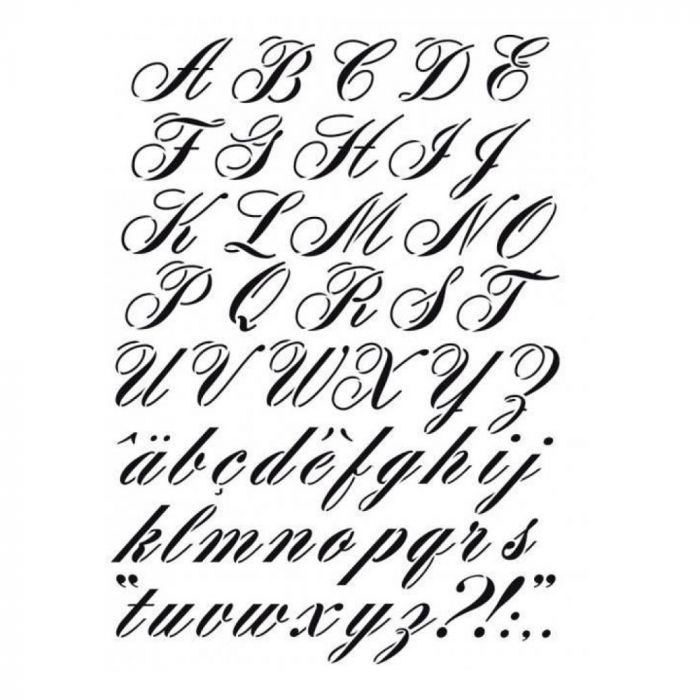
Police d'écriture italique
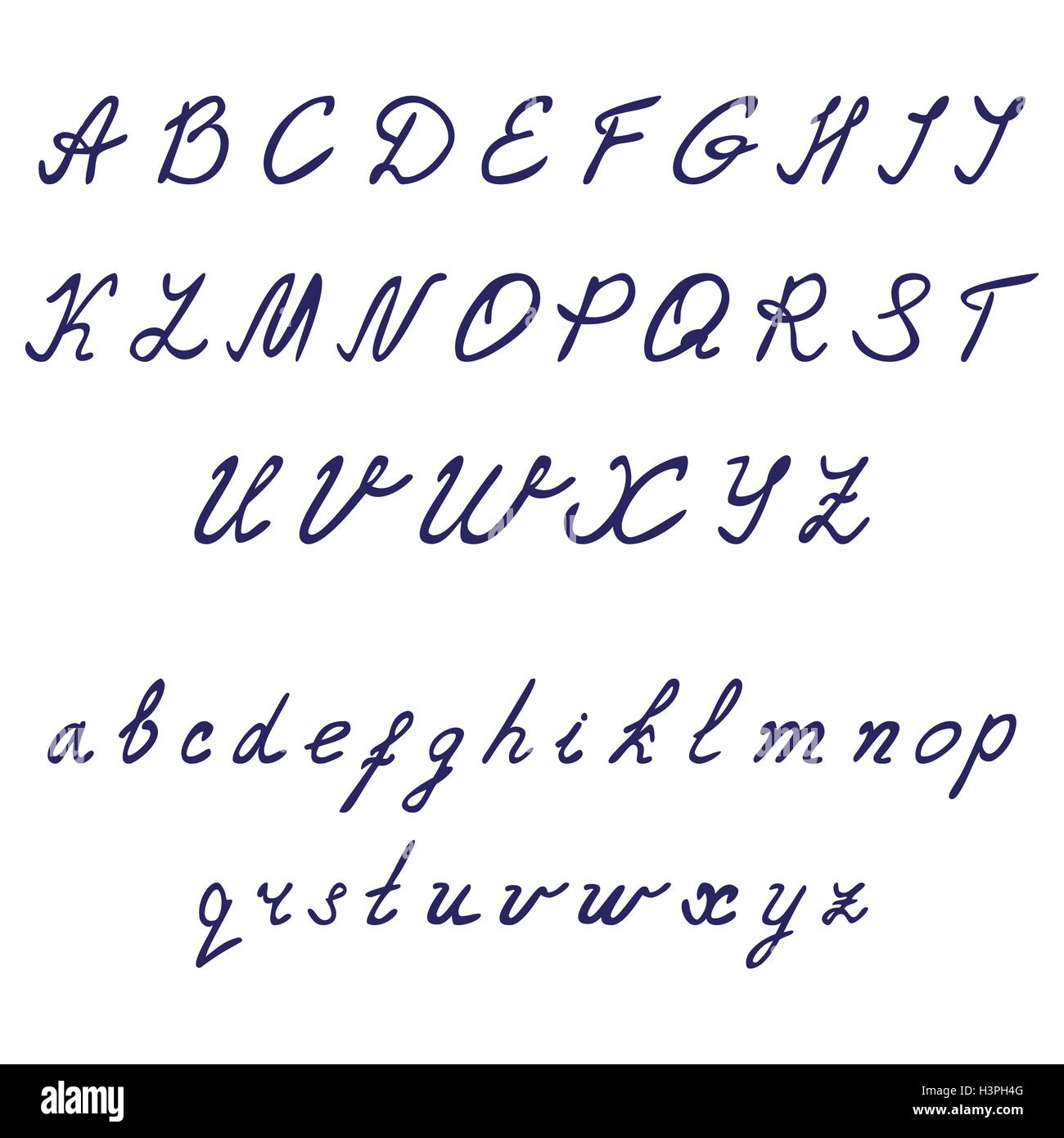
Police Mediaeval Italique
Polices cursives, italiques et inclinées
En effet, elles gardent une trace de l’outil utilisé pour écrire (plume ou stylo), quand la main de l’écrivain se relève pour . Des traits fins, des lettres simples, des courbes élégantes, c’est la police «Caviar Dreams». For commercial use, kindly donate me (pay as you want .Critiques : 197DaFont - Polices à téléchargerdafont. :: Informations sur la police. La police en italique. Les différentes versions de la police Cooper Hewitt Thin sont idéales pour un rapport d’entreprise car elles offrent une combinaison simple et .
Design With FontForge: Italique
Eh oui, le célèbre outil de créations graphiques vous aide également à choisir les meilleures combinaisons de polices pour votre site.
Super cool texte unicode texte magique. 9 389 284 téléchargements (2 330 hier) 177 commentaires 100% Gratuit - 16 fichiers.Le style italique est probablement celui qui est le plus mal compris dans le design de polices, mais il est celui avec le plus grand potentiel d’enthousiasme et de plaisir en .